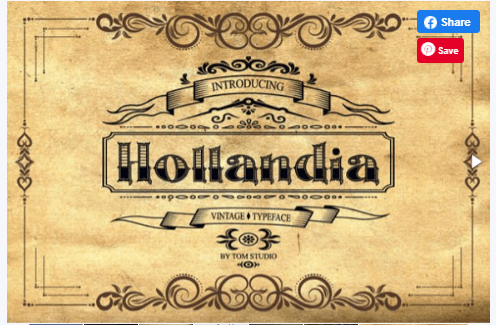
Hollandia Font
Hollandia - это жирный шрифт в винтажном стиле. Этот впечатляющий шрифт имеет буквы уникальной формы, и в результате он легко сочетается с широким спектром творений, требующих особого подхода.